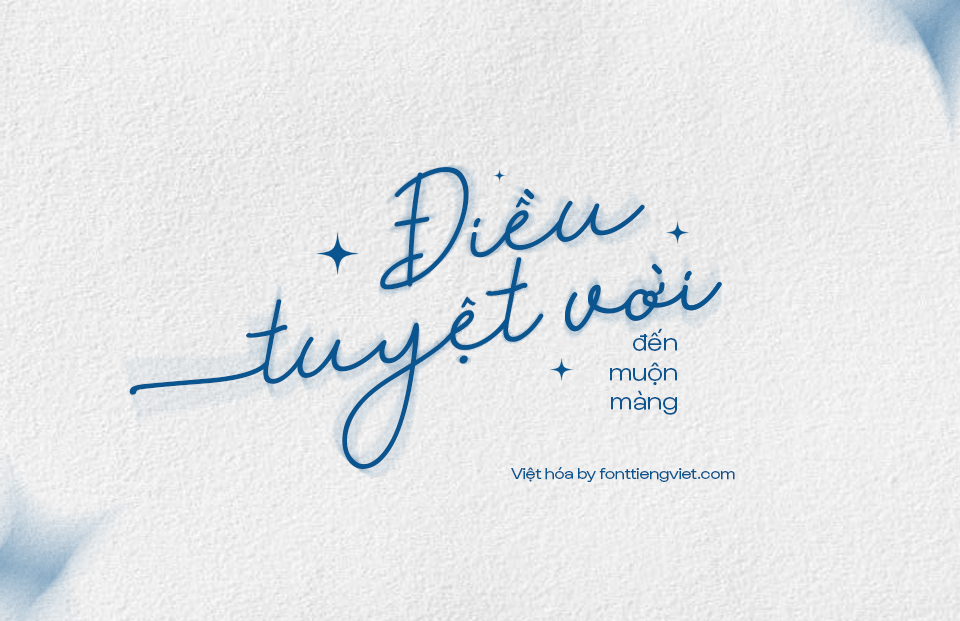
Giới thiệu về Font Việt hóa 1FTV VIP Diaseli Signature
Trong thế giới đồ họa hiện đại, việc tìm kiếm một mẫu Font Chữ mang đậm dấu ấn cá nhân luôn là ưu tiên hàng đầu của các nhà thiết kế. Font Việt hóa 1FTV VIP Diaseli Signature chính là giải pháp hoàn hảo cho những ai yêu thích phong cách chữ ký phóng khoáng và sang trọng. Đây là bộ font được tinh chỉnh kỹ lưỡng, hỗ trợ đầy đủ tiếng Việt giúp bạn truyền tải thông điệp một cách mềm mại nhất.
Đặc điểm nổi bật của font chữ ký
Mẫu font này sở hữu những đường nét thanh mảnh, kết nối tự nhiên như nét bút thủ công trên giấy. Với cấu trúc linh hoạt, Font Việt hóa 1FTV VIP Diaseli Signature giúp các ấn phẩm truyền thông trở nên chuyên nghiệp và gần gũi hơn bao giờ hết.
Ứng dụng thực tế của Font Việt hóa 1FTV VIP Diaseli Signature
Bộ font này cực kỳ phù hợp cho các dự án thiết kế logo, danh thiếp hoặc thiệp mời sự kiện cao cấp. Ngoài ra, các bạn học sinh có thể sử dụng font để làm bài thuyết trình thêm sinh động và bắt mắt.
Lợi ích khi sử dụng font Việt hóa
Việc sử dụng bản Việt hóa giúp loại bỏ hoàn toàn lỗi hiển thị dấu tiếng Việt, đảm bảo tính thẩm mỹ đồng nhất cho văn bản. Bạn có thể tự tin sáng tạo mà không lo lắng về vấn đề kỹ thuật font chữ.